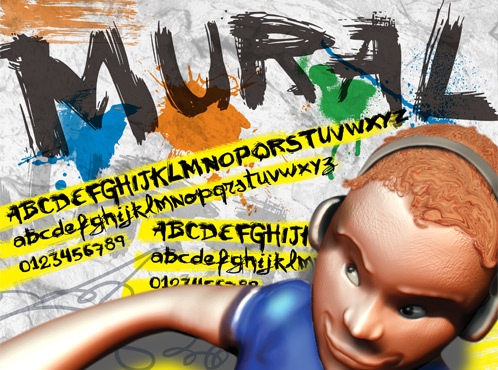
VTKS Mural, di Douglas Vitkauskas, è un font graffiti gratuito in stile "trash" che cattura il segno crudo della street art dipinta a mano. Le maiuscole sembrano tracciate con un pennello carico, tra bordi irregolari, strisciate secche e una pressione irregolare che conferisce all'intero set un'energia rapida da muro di strada.
È perfetta per flyer musicali, grafiche skate, branding streetwear, poster e copertine di zine dove cerchi un lettering che sembri improvvisato piuttosto che rifinito. Essendo un font gratuito, funziona bene anche per titoli brevi, cartelli e monogrammi grezzi, perché i caratteri trasmettono un ritmo pittorico forte anche in poche parole.